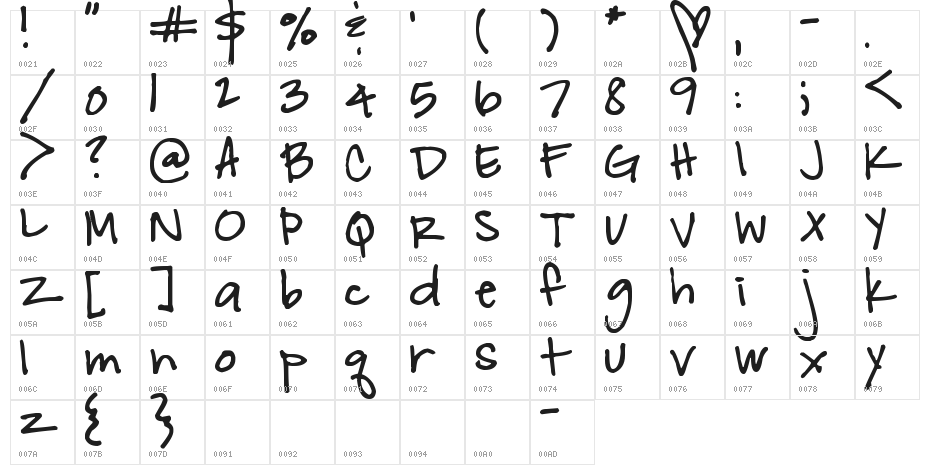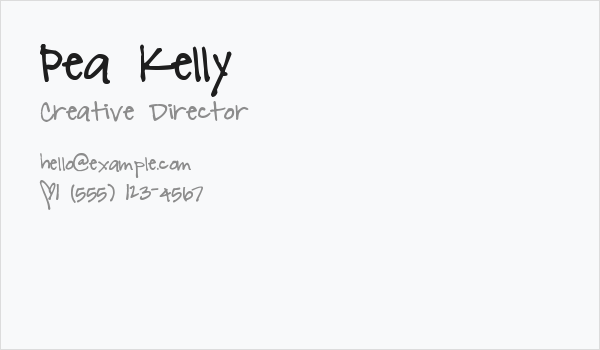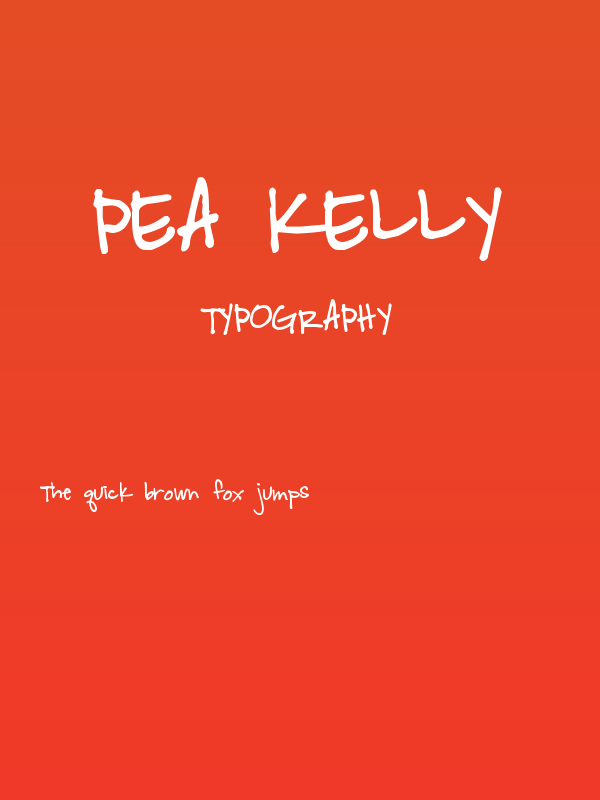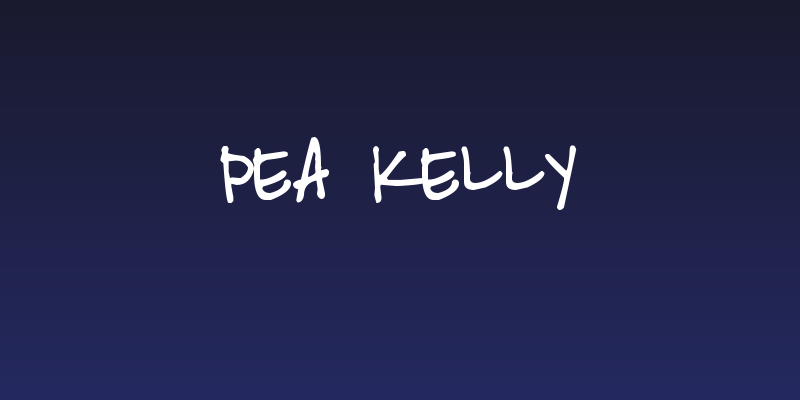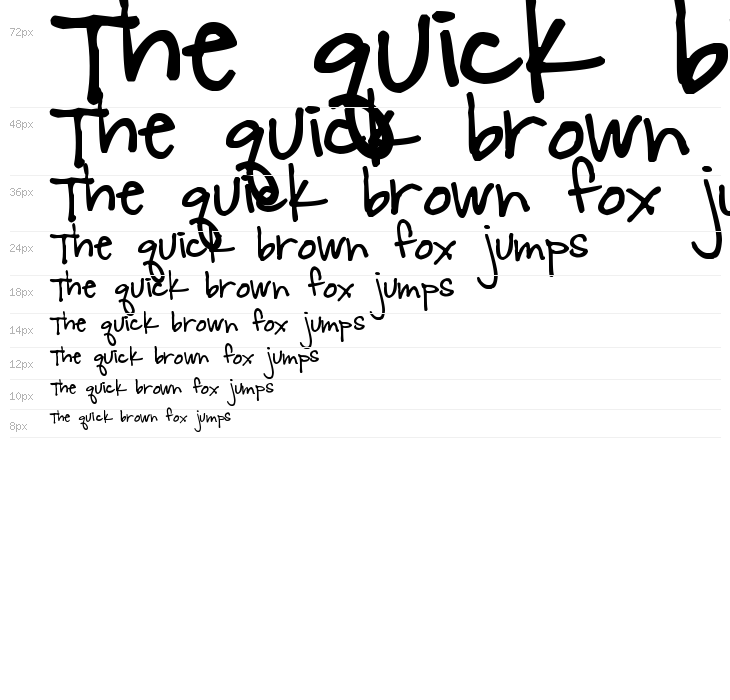
Pea Kelly Font
| Estilo general | Casual |
| Caso de uso | Headlines, Informal text, Creative projects |
| Proyectos propuestos | Ideal for greeting cards, personal blogs, children's books, and informal branding. |